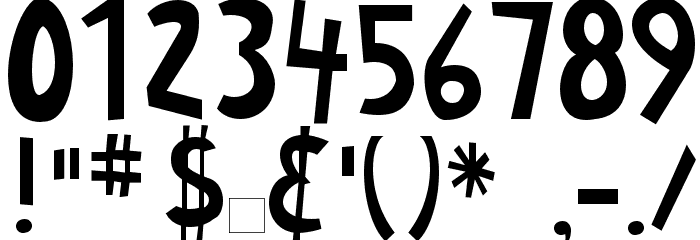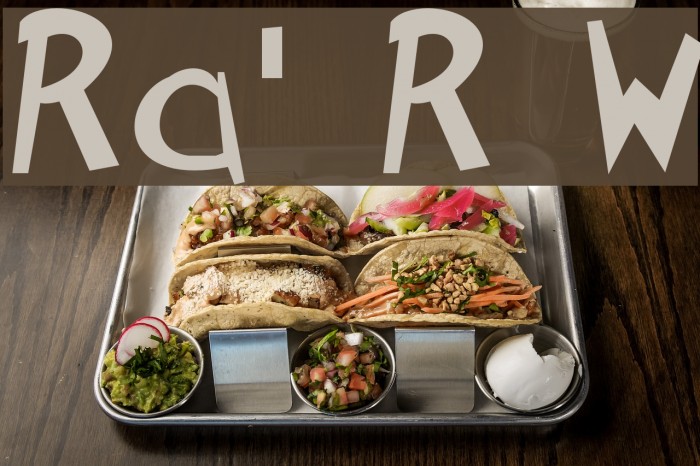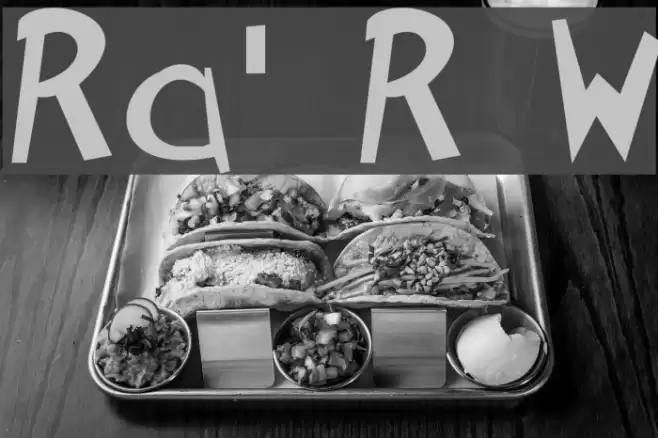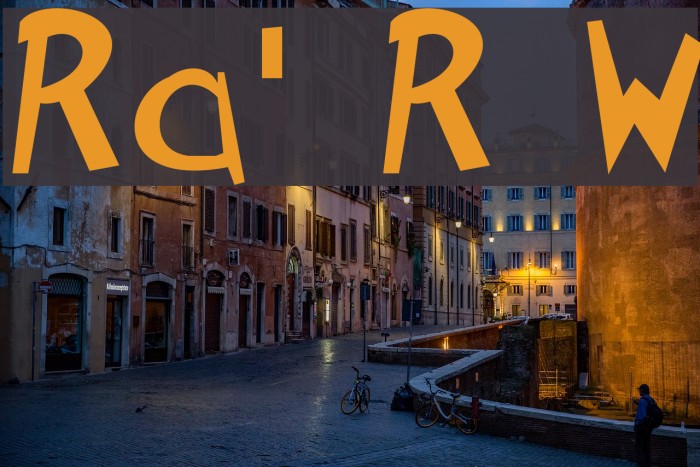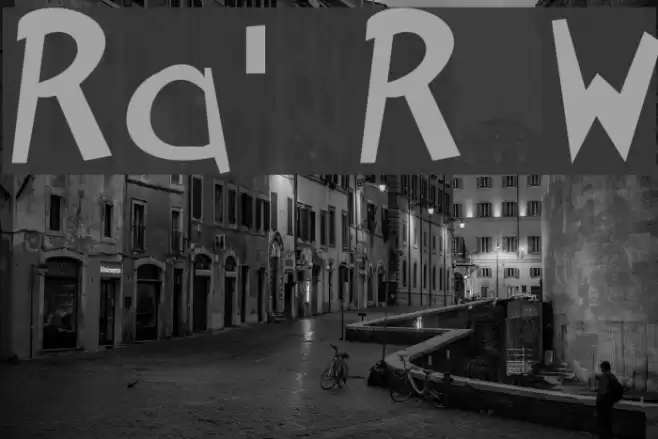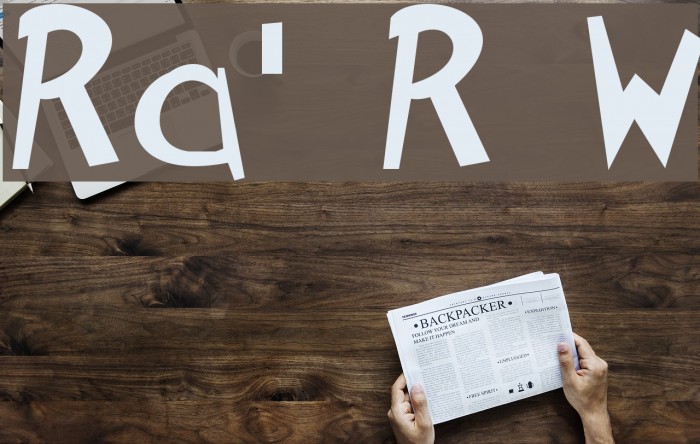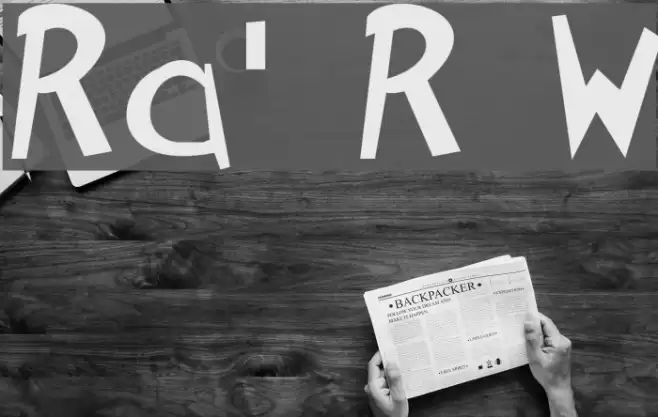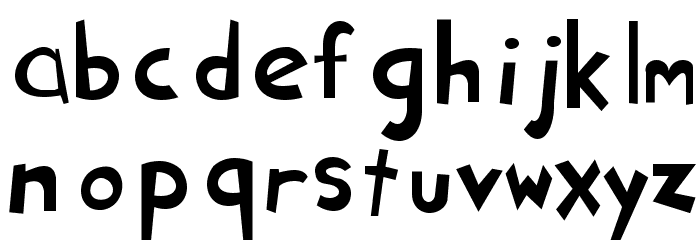
Ryan's Rotten Writing Font
| Vorgeschlagene Projekte | Ideal for children's books, comic strips, playful branding, and creative posters. |
Ryan's Rotten Writing